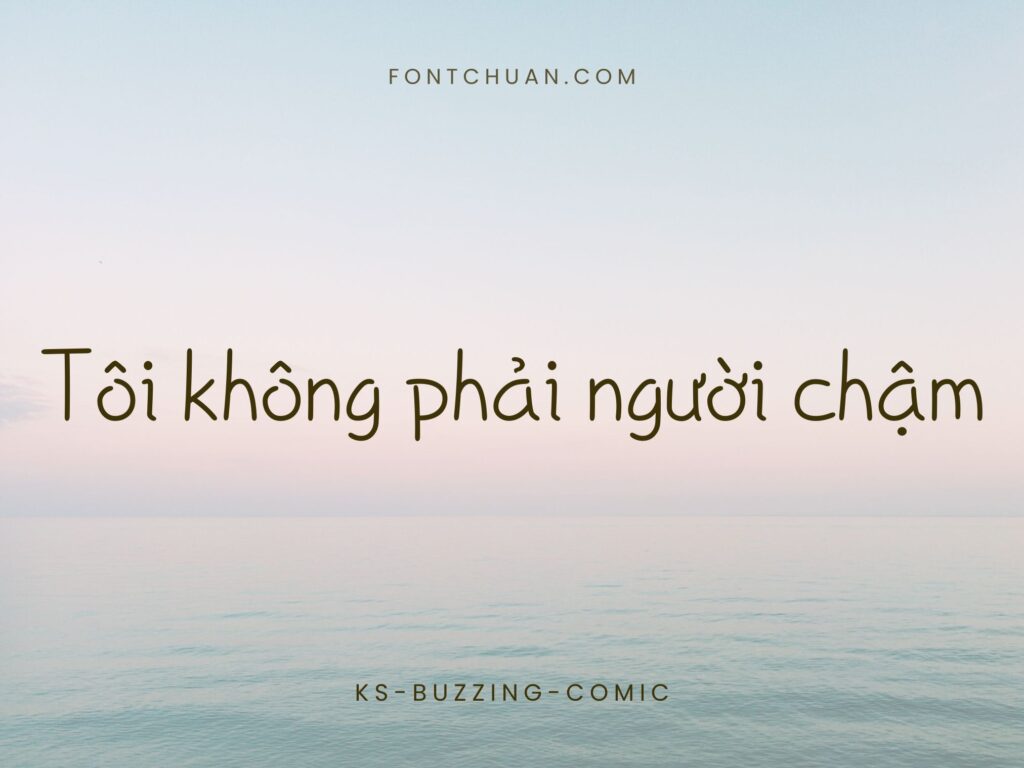
Font Ks Buzzing Comic Việt Hóa
Buzzing Comic là một phông chữ thuộc nhóm Font Display và sans-serif, được thiết kế với phong cách vui nhộn và thân thiện, lấy cảm hứng từ các chữ cái trong truyện tranh. Phiên bản Việt hóa của font này được thực hiện bởi KS Font, hỗ trợ đầy đủ các ký tự tiếng Việt và nhiều ngôn ngữ khác, giúp người dùng dễ dàng ứng dụng vào các dự án thiết kế tại Việt Nam và quốc tế. Thành viên Font Chuẩn đã chọn lọc và sưu tầm font này nhằm đáp ứng nhu cầu bạn đọc, đặc biệt cho các thiết kế sáng tạo, sinh động và vui nhộn.
Về đặc điểm thiết kế, Buzzing Comic có cấu trúc chữ cái đơn giản, dễ đọc, với các đường nét mềm mại và độ dày đồng đều. Phông chữ này tạo cảm giác thân thiện và gần gũi, phù hợp cho các nội dung hướng đến trẻ em hoặc các thiết kế cần sự vui tươi. Với những đặc điểm trên, Buzzing Comic phù hợp cho các ứng dụng như thiết kế sách thiếu nhi, truyện tranh, áp phích giáo dục, và các dự án sáng tạo khác. Phông chữ này cũng thích hợp cho các thiết kế cần sự thân thiện và vui nhộn, như thiệp mời sinh nhật, bao bì sản phẩm dành cho trẻ em, và các sản phẩm truyền thông xã hội. Về ngành nghề, Buzzing Comic đặc biệt phù hợp với lĩnh vực giáo dục, giải trí, và các ngành nghề liên quan đến trẻ em. Sự linh hoạt và tinh tế của phông chữ giúp nó dễ dàng hòa nhập vào nhiều phong cách thiết kế khác nhau, từ cổ điển đến hiện đại.